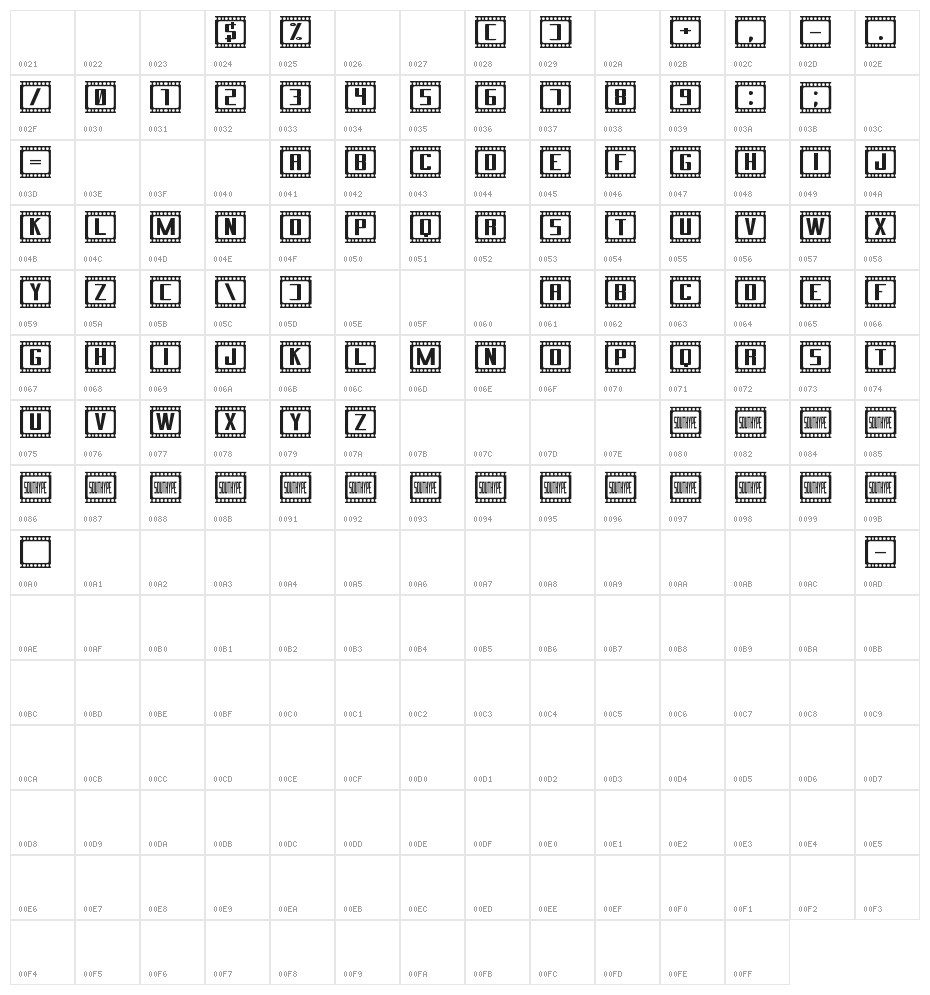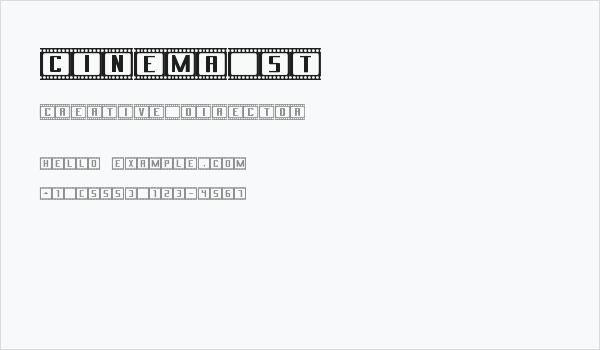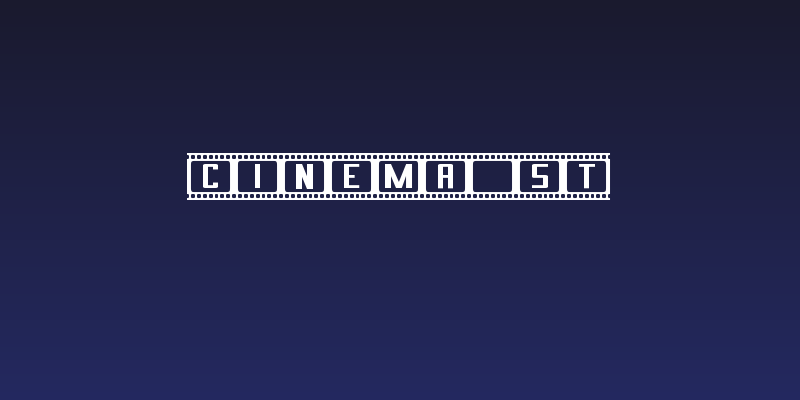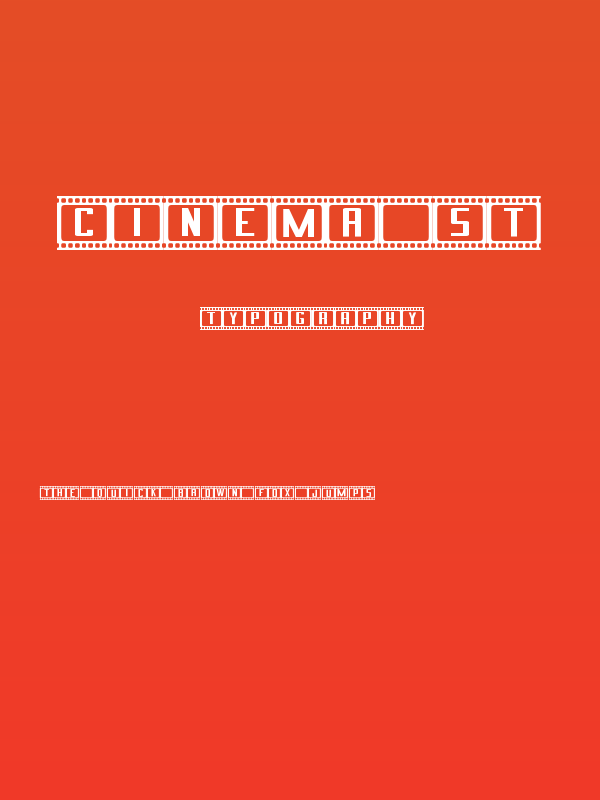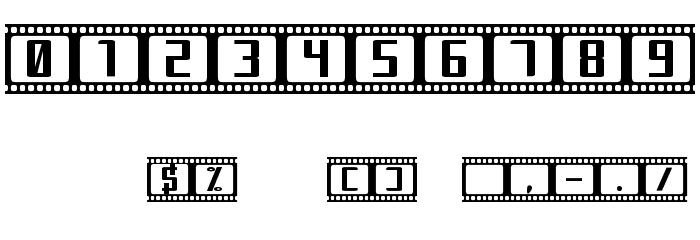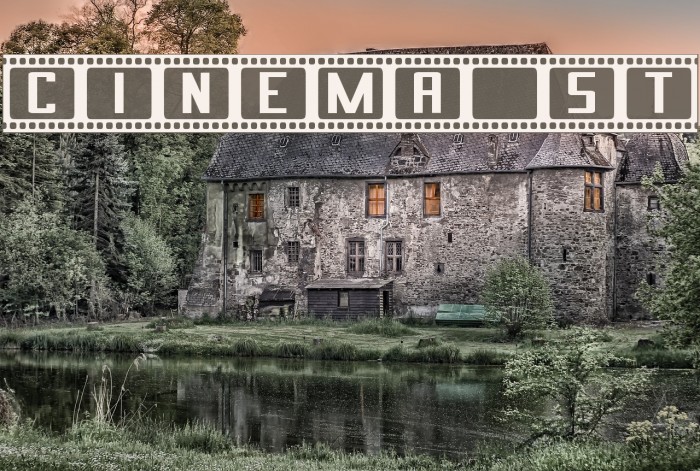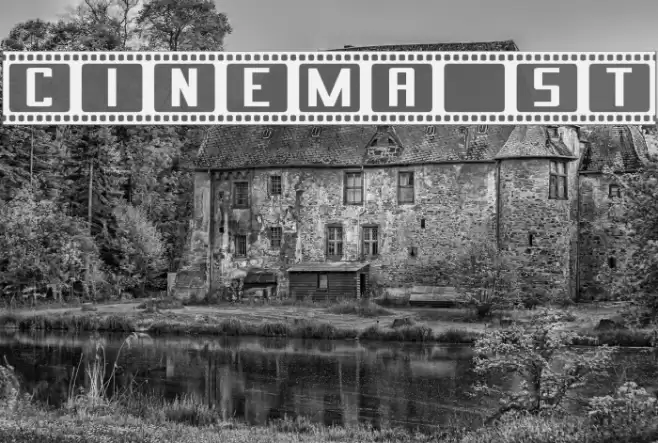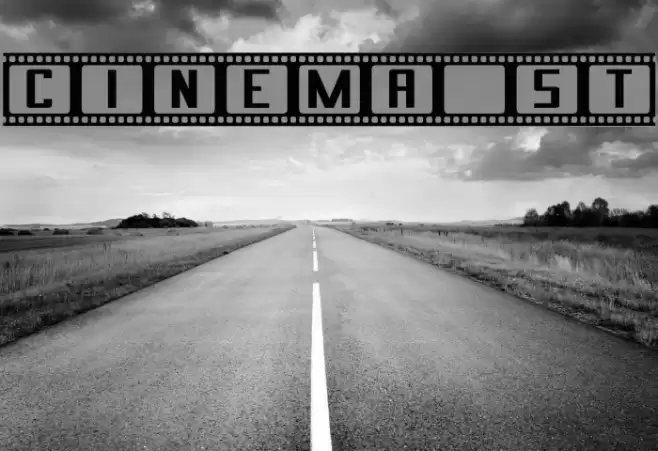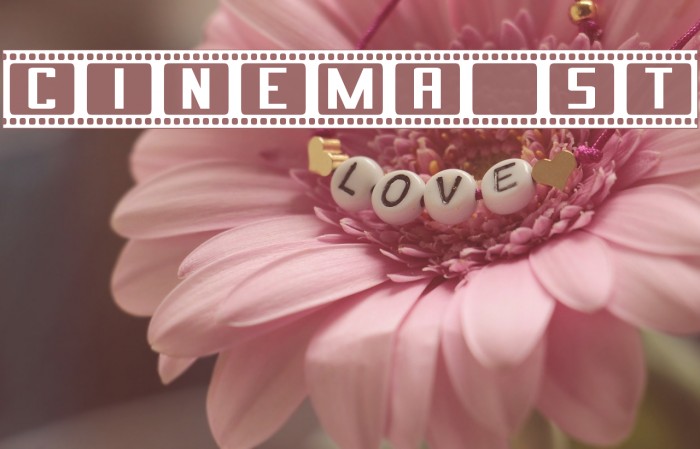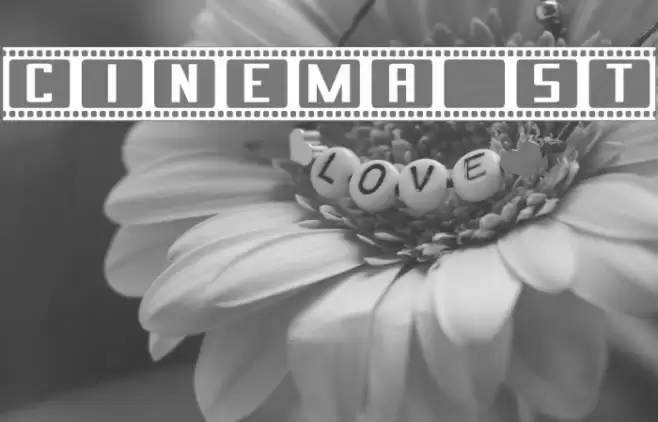
Cinema St Font
✎ Decorative
| Kategorien | Decorative |
| Gesamtstil | Vintage |
| Vorgeschlagene Projekte | Ideal for movie posters, film festival branding, retro-themed designs, and entertainment industry logos. |